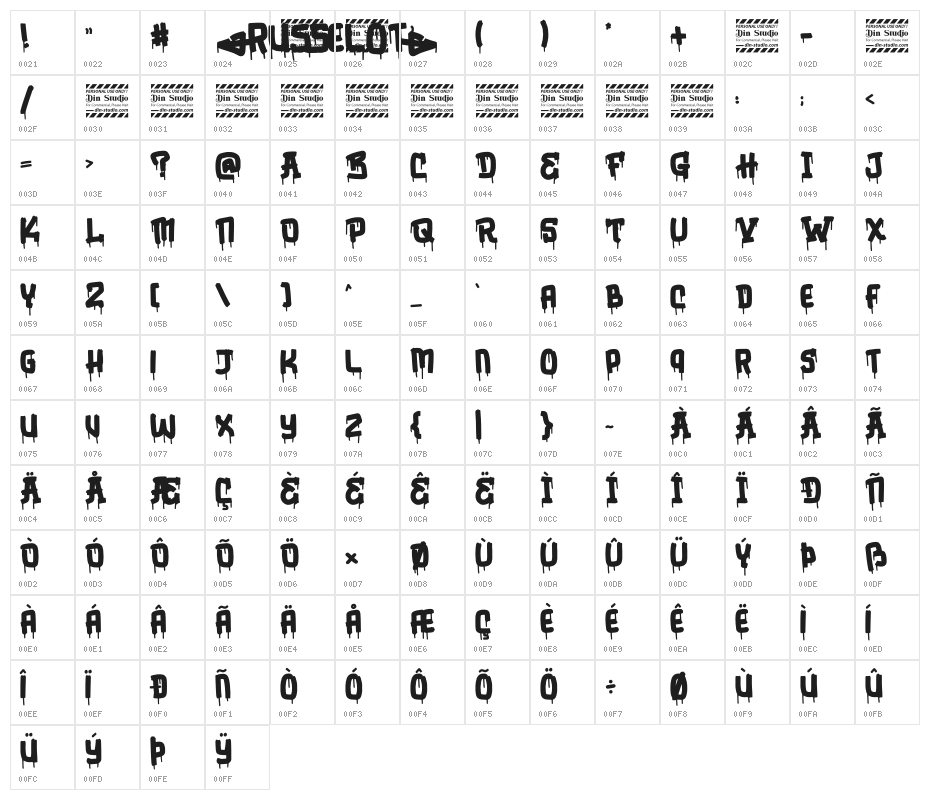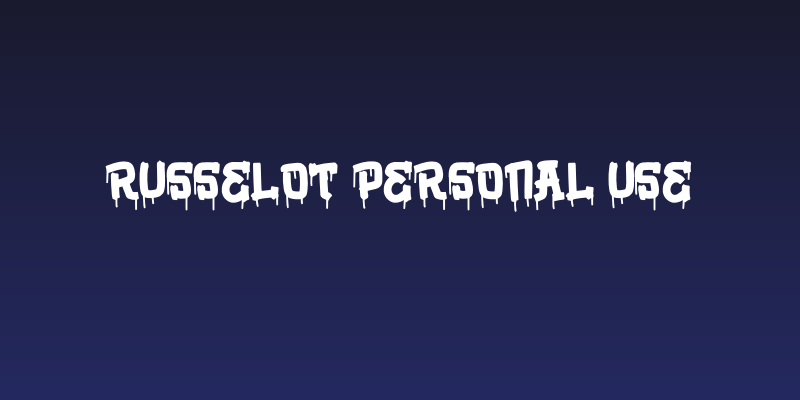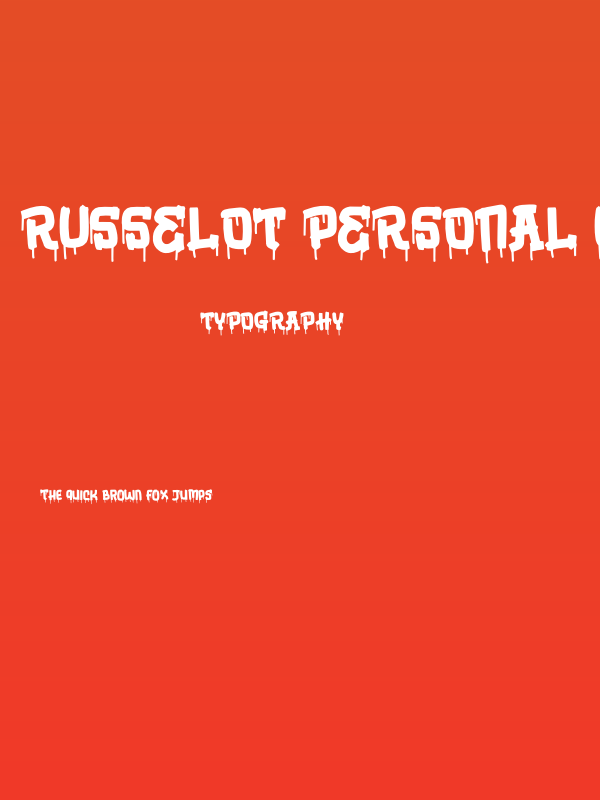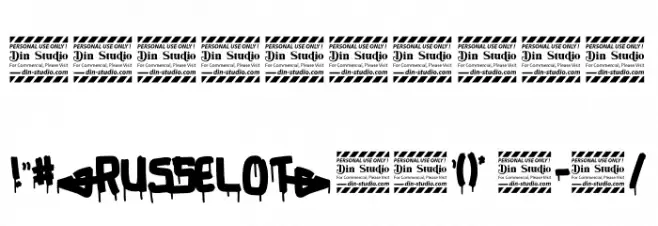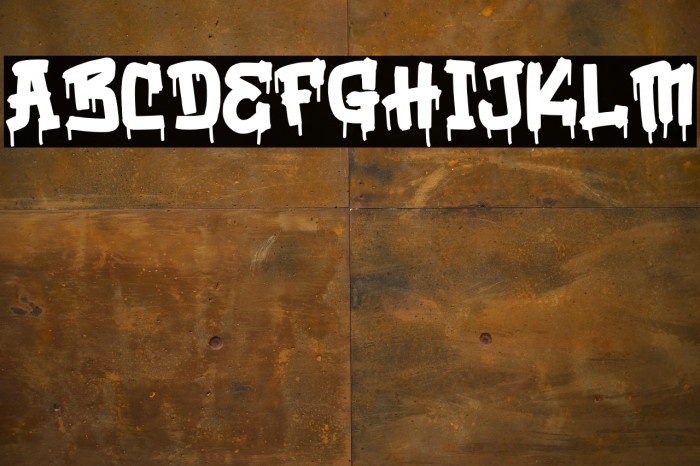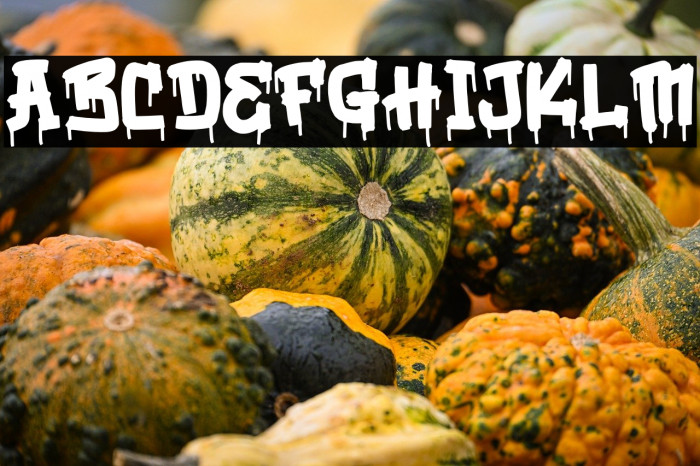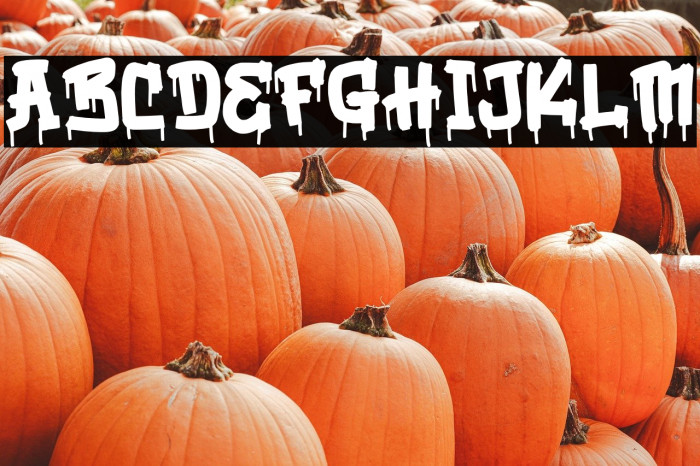
Russelot Personal Use Font
✎ Graffiti
| Gesamtstil | Urban, Graffiti, Bold |
| Vorgeschlagene Projekte | Ideal for street art designs, music album covers, event posters, and urban-themed branding. |